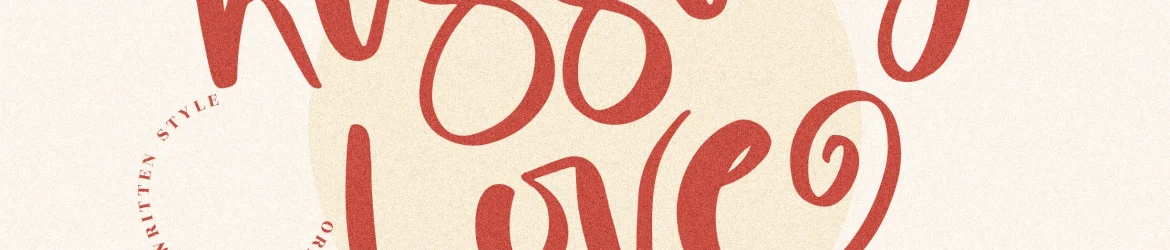
Kissing Love Font – Download Grátis
Esta é uma fonte escrita à mão ideal para uma ampla variedade de projetos, desde logomarcas até convites de casamento, passando por tags de embalagens e fotografias. Com sua textura natural e agradável ao toque, esta fonte perspectype Kissing Love pode revestir qualquer projeto que desejamos dar um ar delicado e pessoal. Seja para marcar homens de luxo ou obras de arte em livros, as letras escritas à mão da perspectype Kissing Love oferecem a perfeita dose de autenticidade e personalização que você precisa. Suas linhas suaves, contornos fluidos e entrelaçamentos delicados criam um visual que transmite conforto e confiança sem deixar de ser encantador. A perspectype Kissing Love é uma fonte perfeita para aqueles projetos onde você deseja incorporar o toque delicado de uma escrita à mão em seus designs, tornando-os únicos e memoráveis.